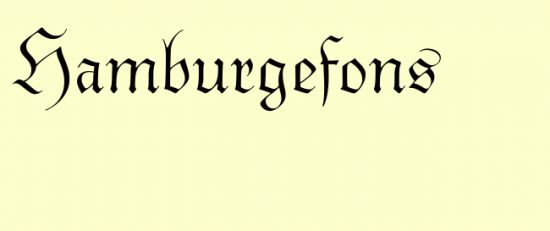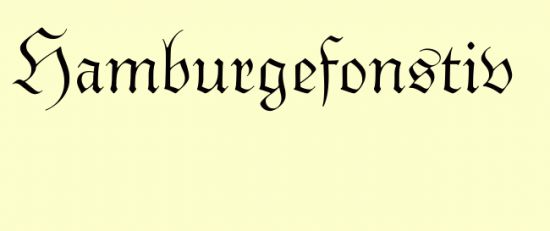
Nike hat's - Glückwunsch.
Schwere Geburt, was?
Und quod erad demonstrandum zur Hamburgefons-Diskussion:
Ich gebe zu, Eriks Kunstwort sieht hübscher aus.
Aber meine Kombination am Schluß empfinde ich zum Klassifizieren dennoch als wertvoller.
Nike, Du bist dran.
das war ne echte fleissarbeit sich durch alle blackletter durchzuwühlen =(
genau.
e: damit es nicht ganz so lang dauert wie beim letzten, hier noch ein weiterer buchstabe.
Ach, Zeit..
Es macht für mich eher den Reiz aus, daß Zeit hierbei keine Rolle spielt.
Wenn ich Schriften klassifizieren muß, vergehen manchmal Wochen, bis ich die Lösung habe.
Zeitdruck = Leistungsdruck
nein.
sie ist vielleicht ein bischen zu neutral. deshalb hier ein anderer buchstabe.
Die Tahoma?
Und die Typeface Six Point Five von Neville Brody?
nein.
vielleicht noch ein paar tipps. sie ist ca. 5 jahre alt, aus europa und nicht bei myfonts gelistet.
die 8 passt nicht ganz.
hier ein weiterer buchstabe.
ein v – VWw sind jedoch ähnlich.
der typedesigner ist relativ bekannt.
bingo. das v ist ziemlich typisch.
CHSC übernehmen sie ;)
Auch die THESIS TheSerif wäre zu einfach ... desweiteren sieht die Serife bei ihr anders aus.
Noch ein zwei Versuche und ich stell ma n neues Bildchen rein.